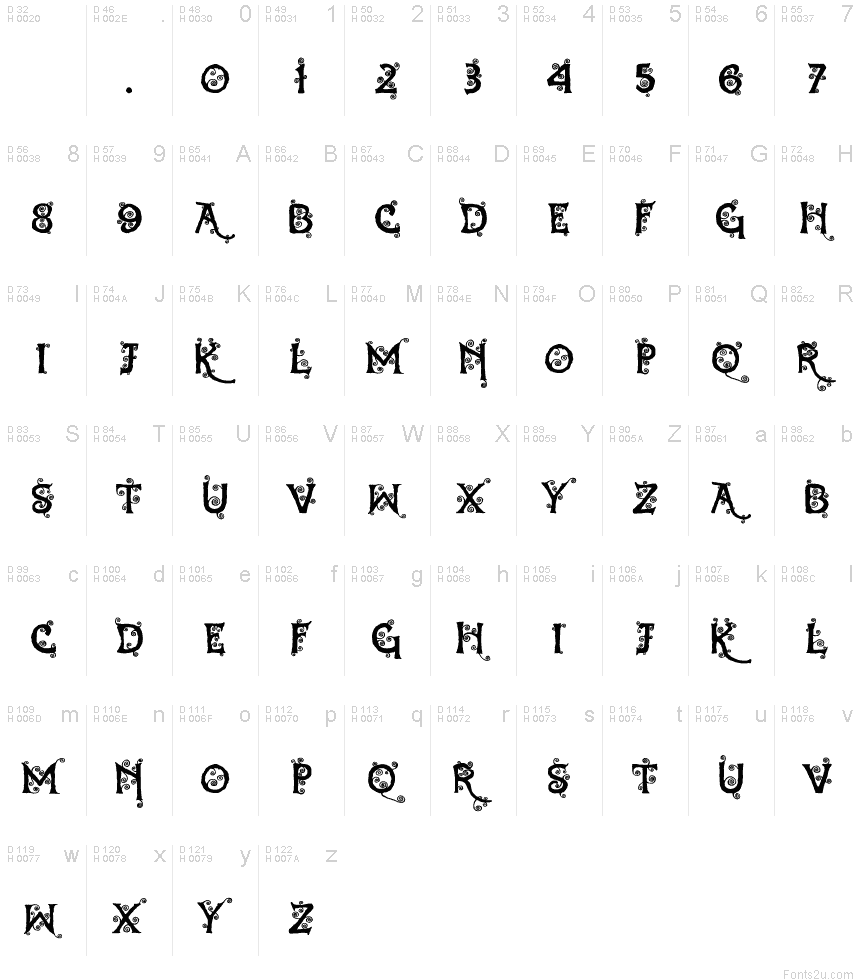
Dearest Dorothy è un font display decorativo gratuito che trabocca di fascino fiabesco e volute che ricordano rampicanti. Ogni lettera sembra disegnata a mano, con vortici d'inchiostro che si arricciano come viticci, conferendo ai titoli un aspetto rigoglioso e incantato. Ha un ritmo vivace che cattura lo sguardo, pur rimanendo abbastanza leggibile da essere colto al volo.
Con Dearest Dorothy, puoi portare la magia delle fiabe su copertine di libri per bambini, inviti, poster fantasy, loghi originali, packaging artigianali e titoli per album. Questo font gratuito dà il meglio di sé nei grandi formati, dove i suoi piccoli riccioli e le sue curve possono essere apprezzati appieno; abbinalo a un semplice sans serif per il testo principale, così da mantenere il layout leggibile e lasciare che le lettere decorate siano le vere protagoniste.
Dearest Dorothy